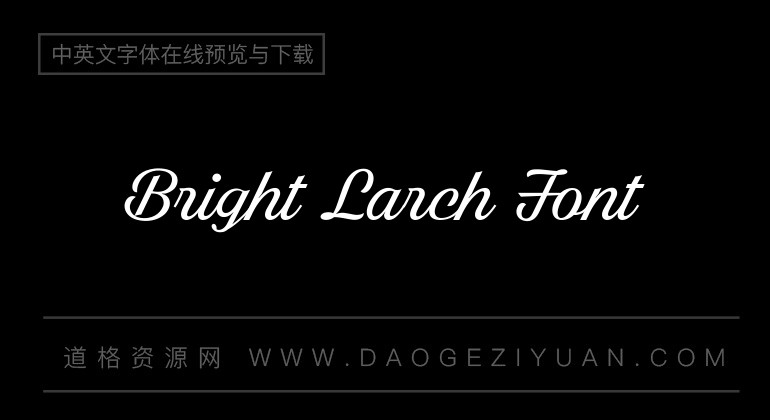
Bright Larch Font 是一种华丽的手写字体,设计师是 Rvq Type Foundry。这种字体的特点是笔画优美,线条流畅,非常适合用于标题和标志设计。它具有一种古老的感觉,但又不失现代感,因此可以适用于多种不同的设计项目。 Bright Larch Font 包括大写字母、小写字母、标点符号和数字。这个字体也非常易于阅读,因为它的线条很清晰,字母之间的间距也很合适。如果您正在寻找一种华丽的字体来增强您的设计,那么 Bright Larch Font 可能是不错的选择。内容介绍
Bright Larch Font是一款非常不错的手写艺术字体,具有很好的视觉感,适合于文化类的宣传设计、商业类品牌的广告和产品包装设计以及个性化文字排版等较多场景。